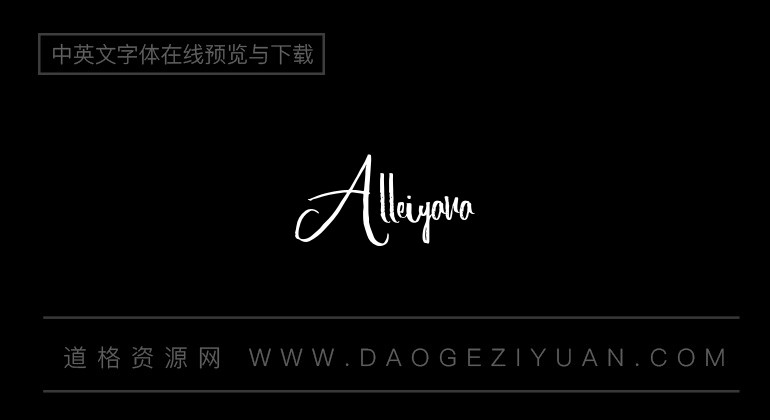
吧 Alleiyana 字体是一款由英国设计师 Alleiyana 创作的字体。Alleiyana 字体具有精致的英文字母,每个字母都有特殊的设计,能够营造出一种精致、温柔的氛围。Alleiyana 字体不仅可以用于文字设计,还可以用于排版、平面设计等。它的设计风格清新、优雅,能够为设计师提供更多的创作灵感。内容介绍
Alleiyana是一款非常不错的手写艺术字体,具有很好的视觉感,适合于文化类的宣传设计、商业类品牌的广告和产品包装设计以及个性化文字排版等较多场景。